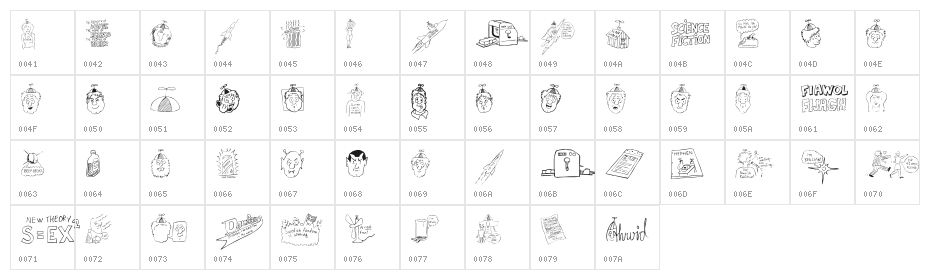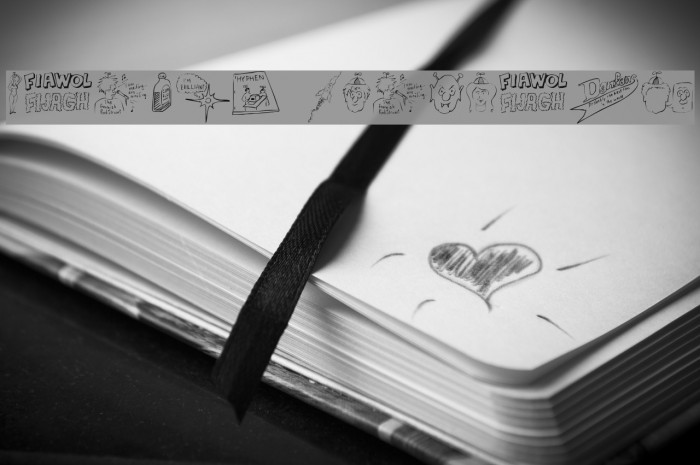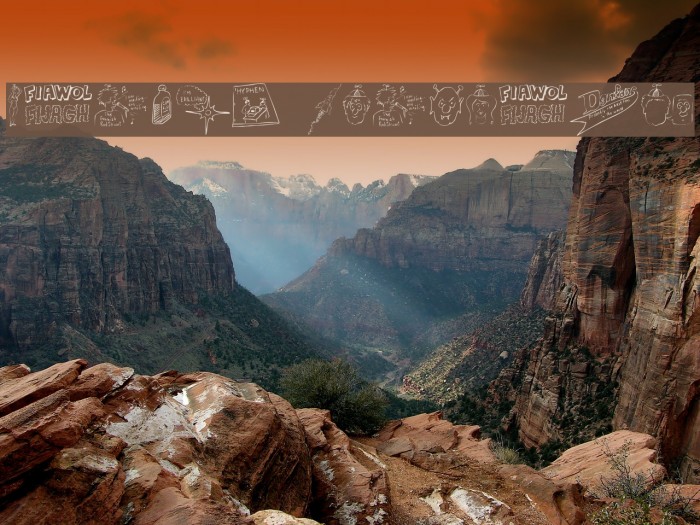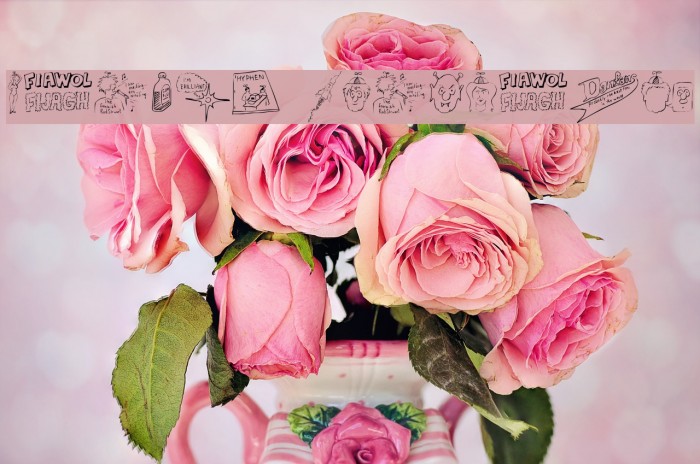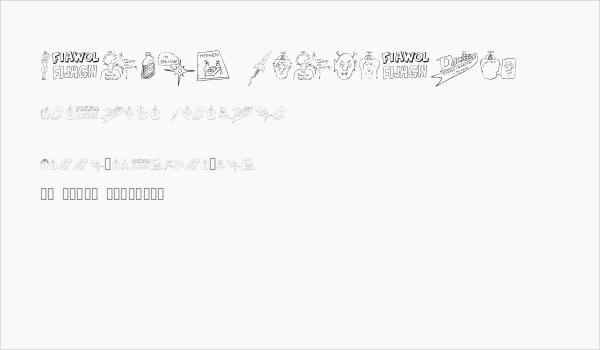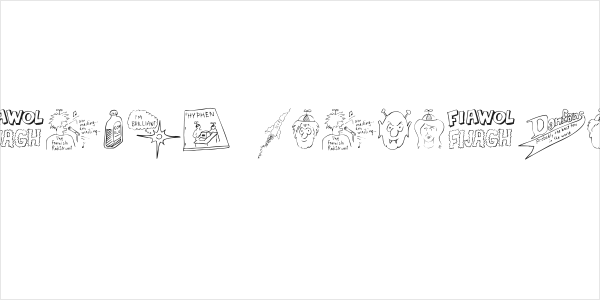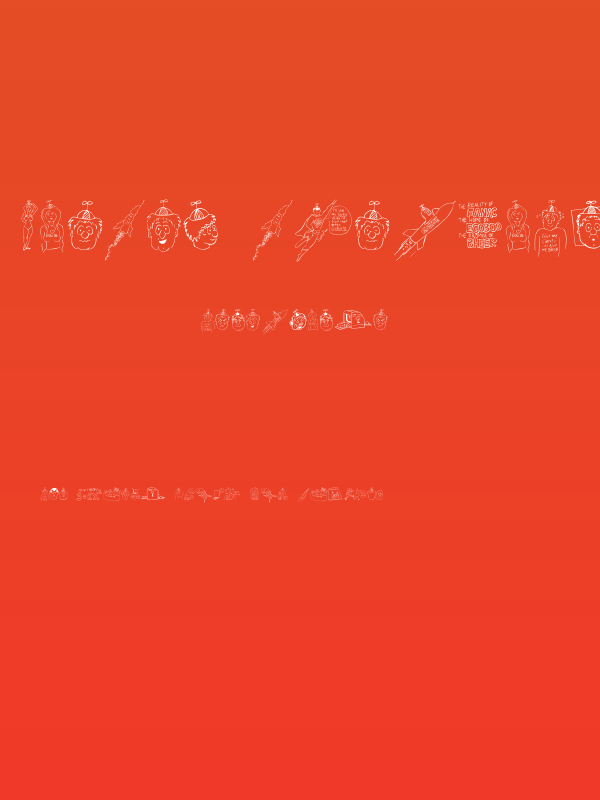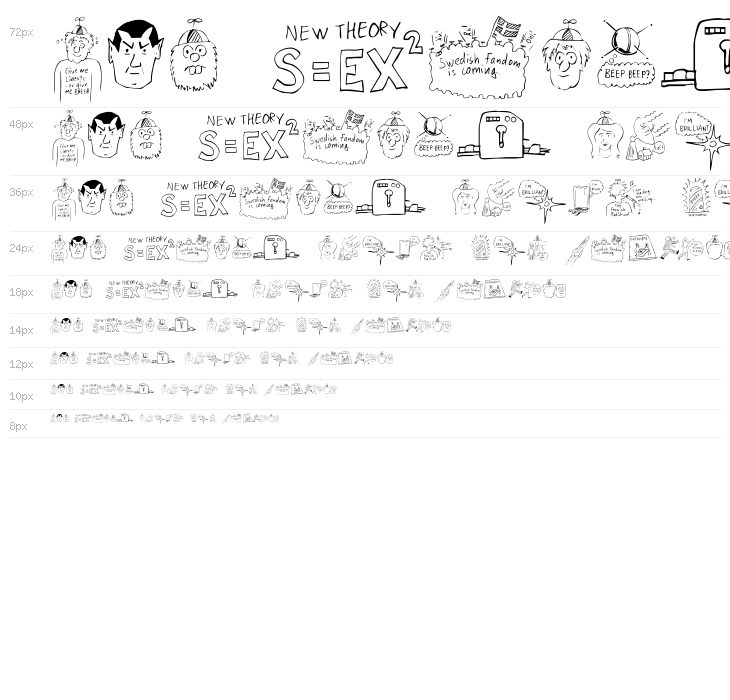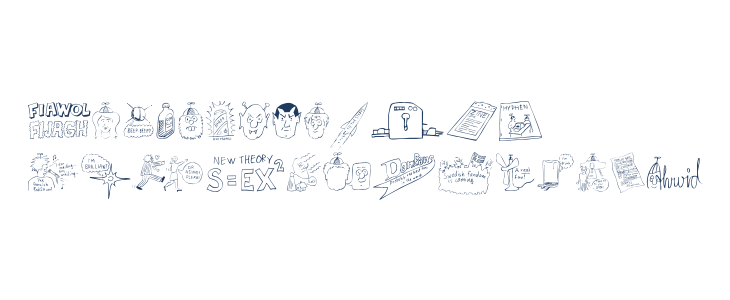
Fandom Dingbats Font
| Stile generale | Cartoonish, Whimsical |
| Caso d'uso | Decorative elements, Themed designs |
| Progetti proposti | Ideal for fan magazines, sci-fi themed party invitations, comic books, and novelty merchandise. |